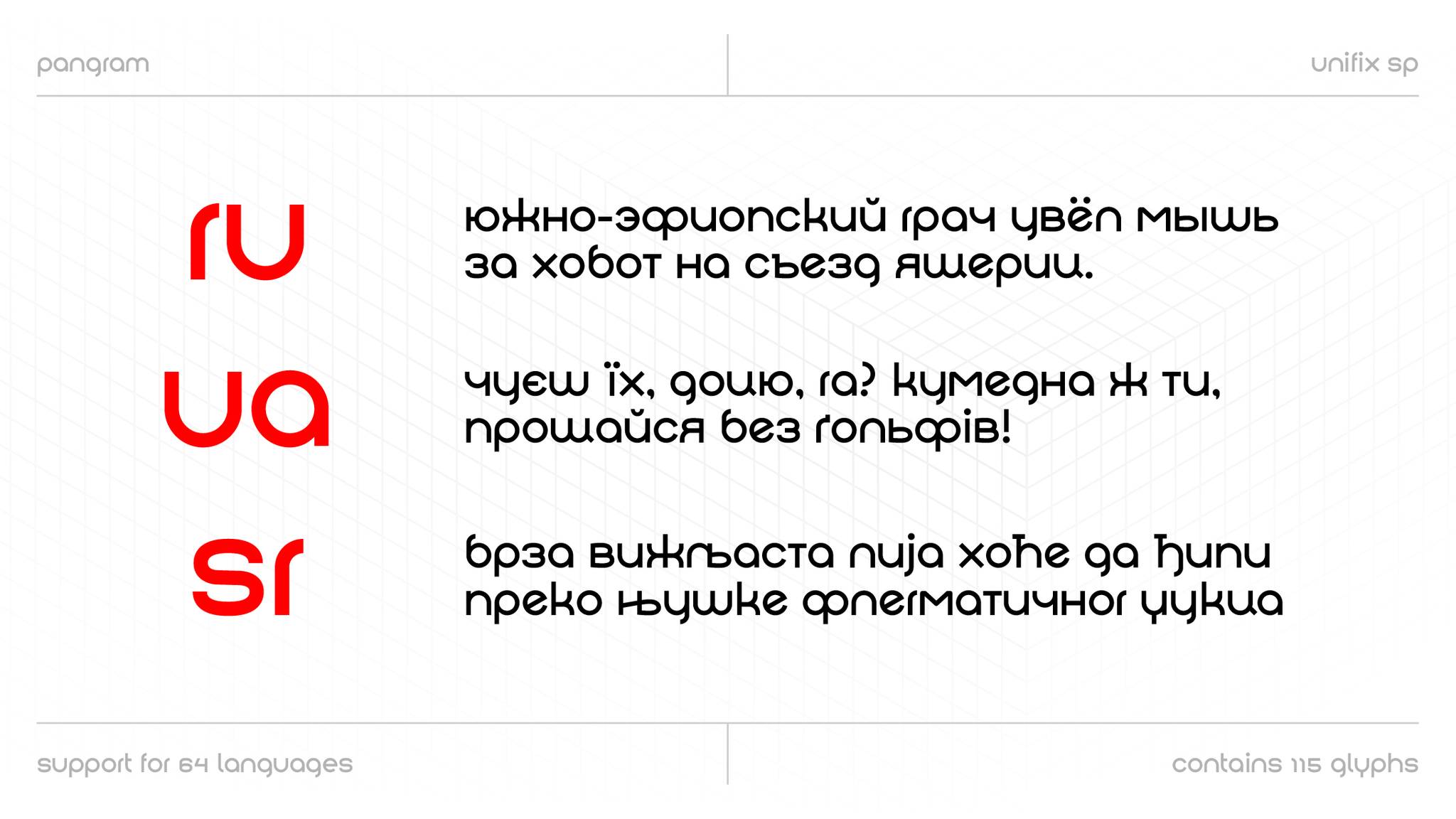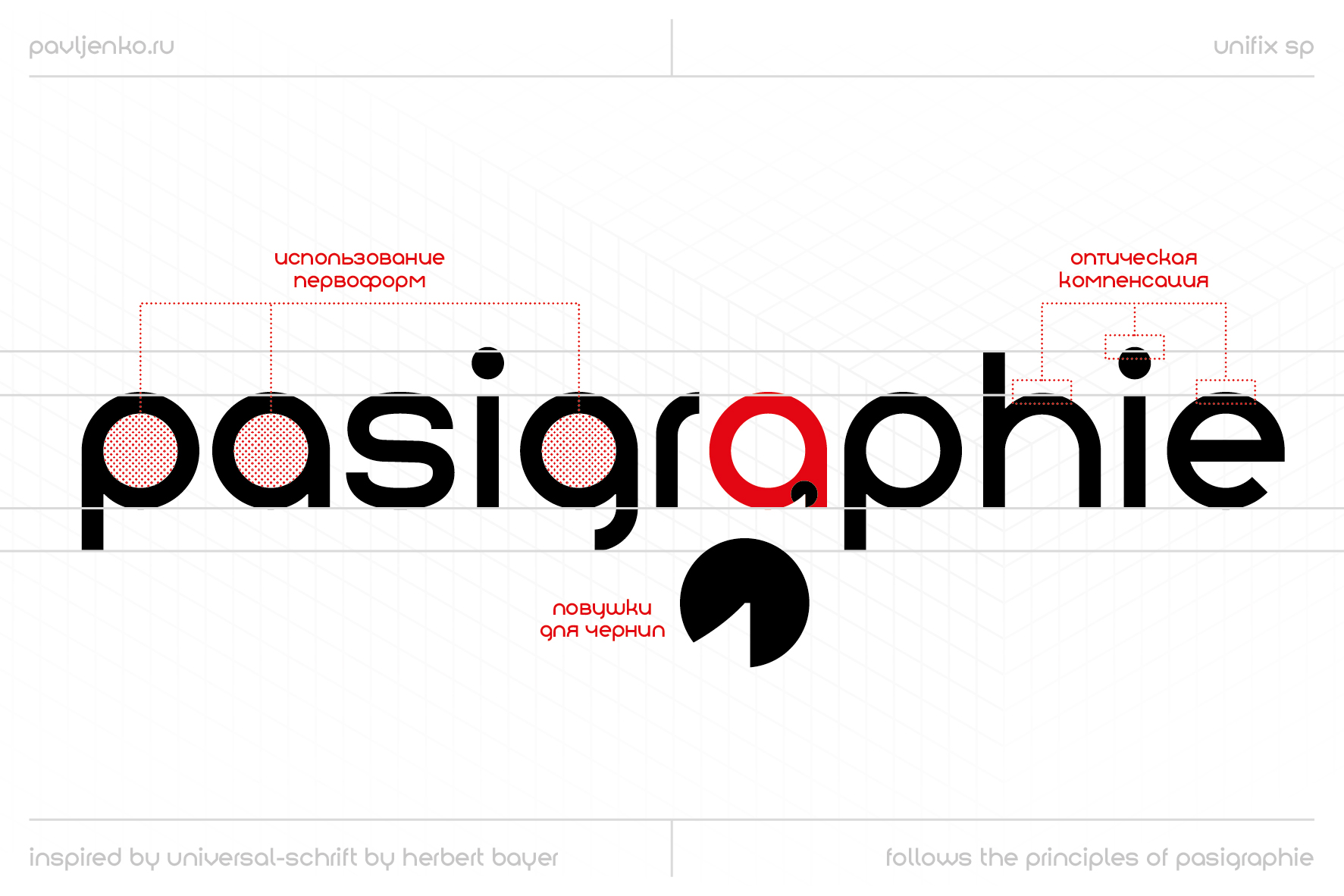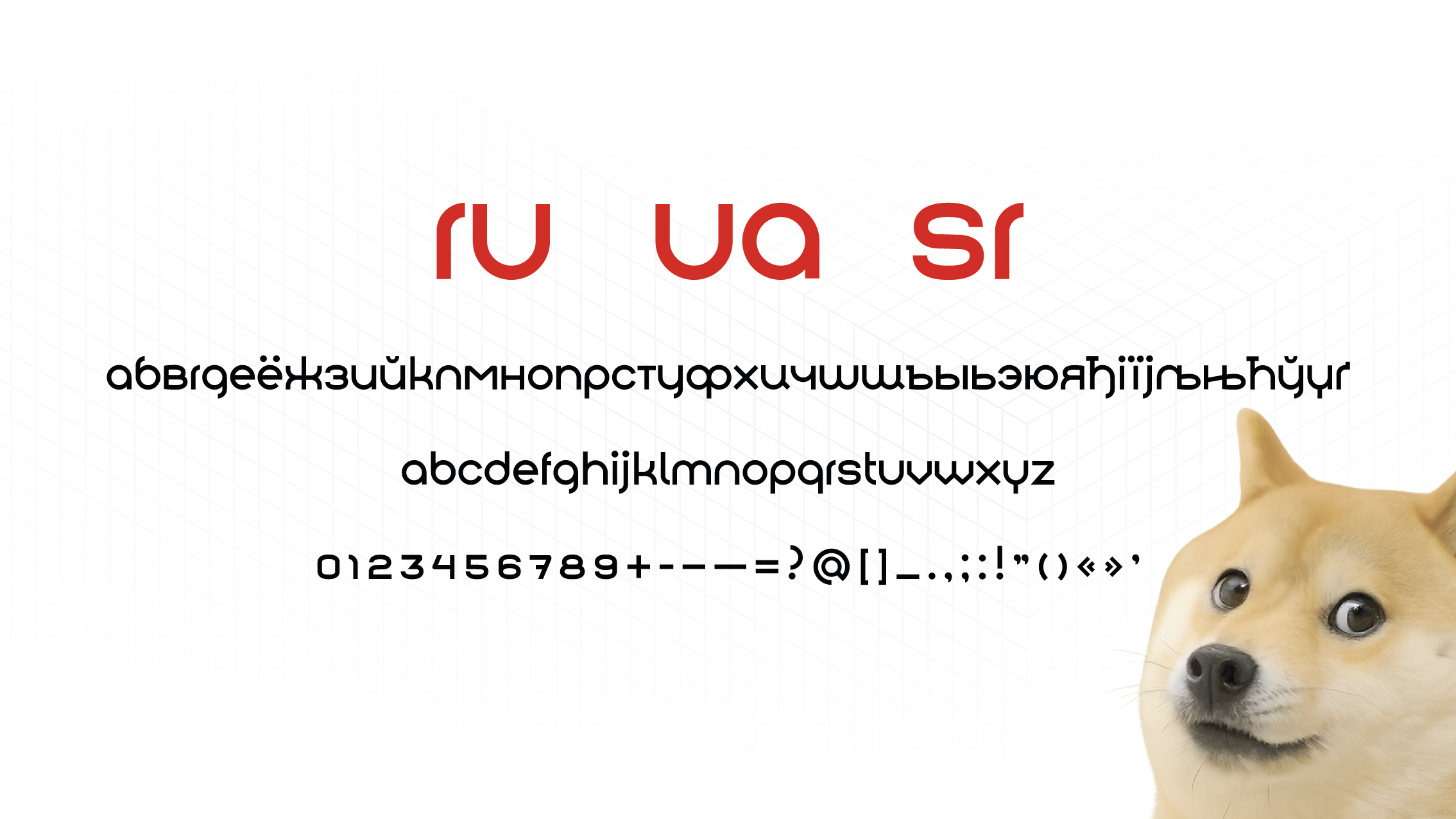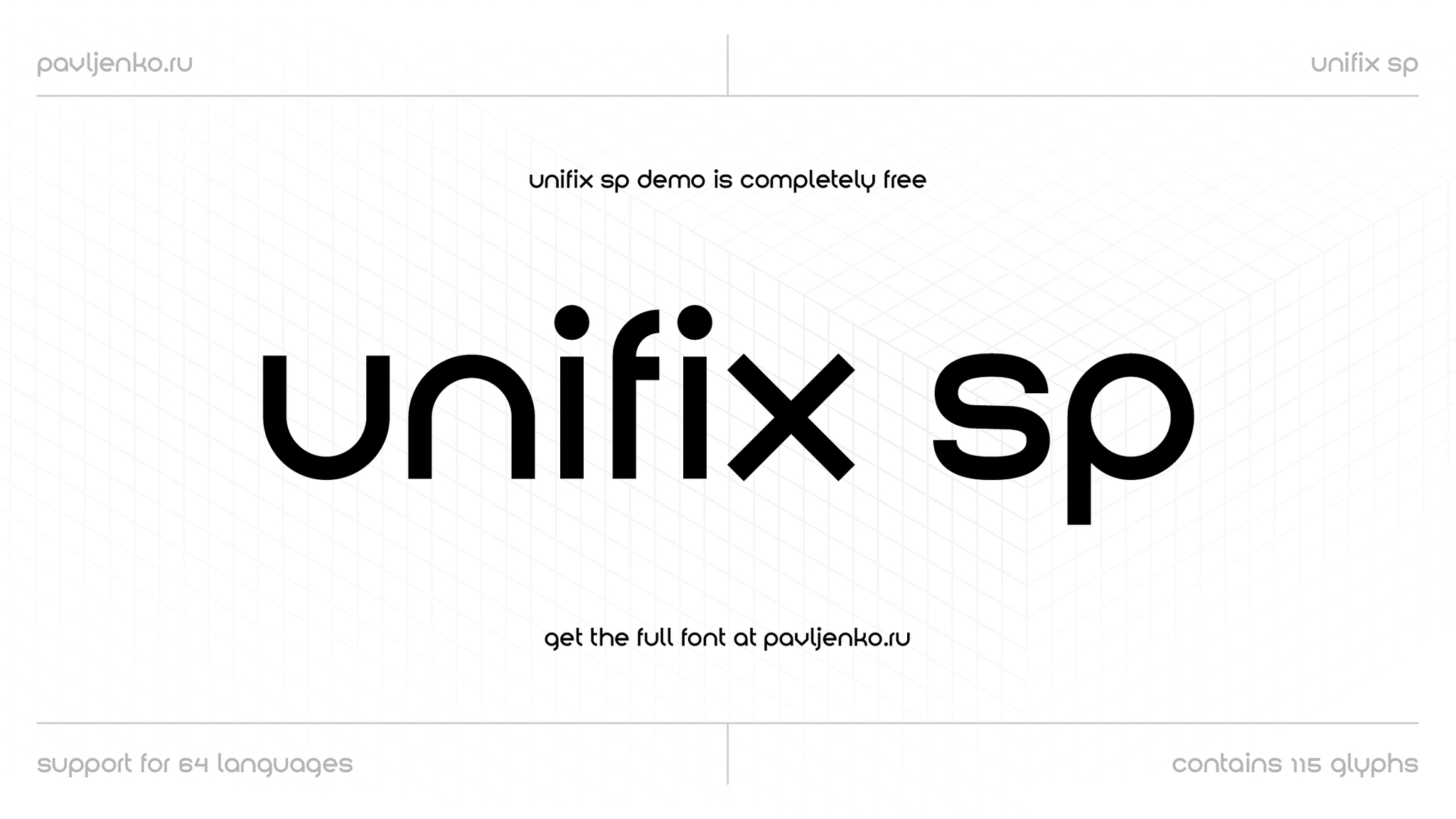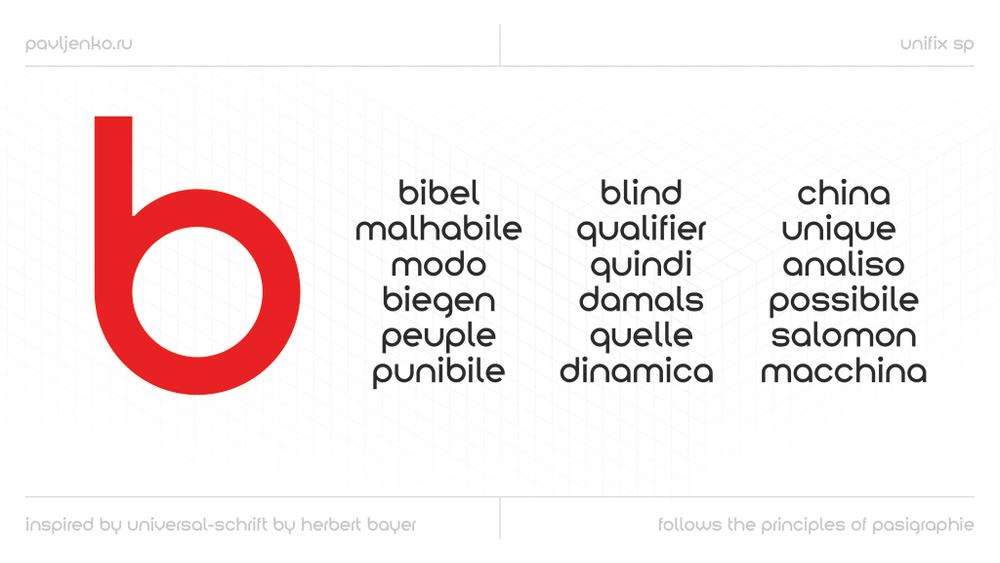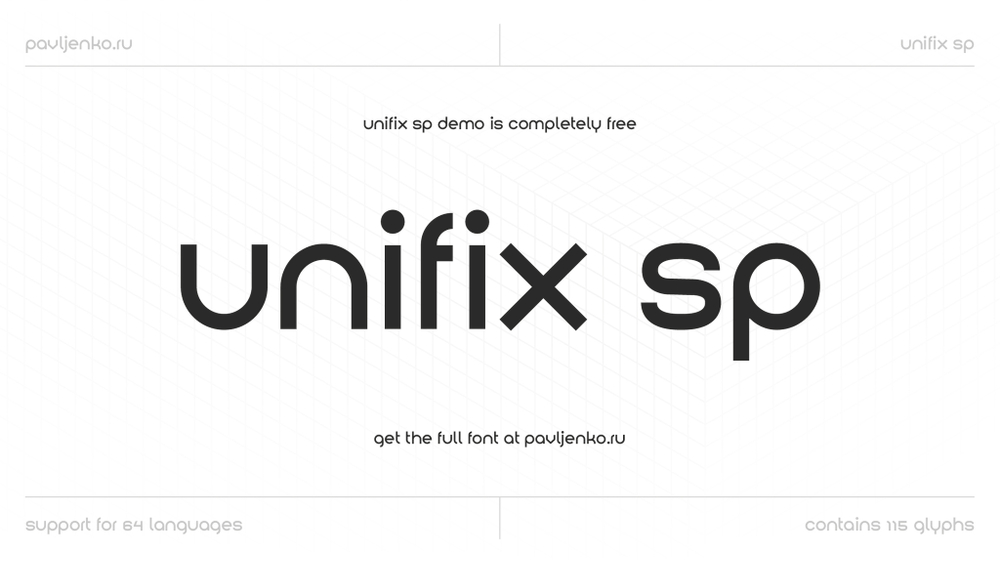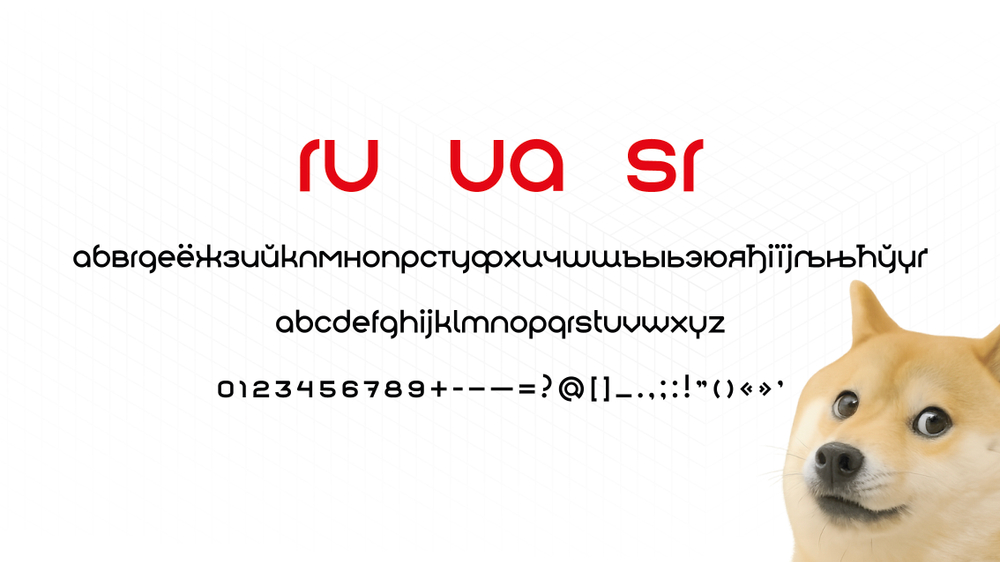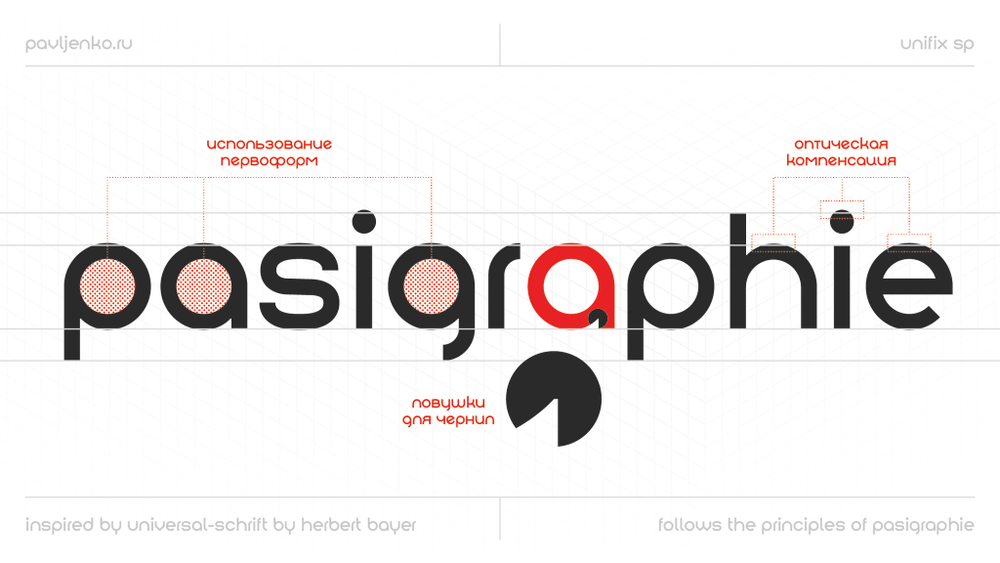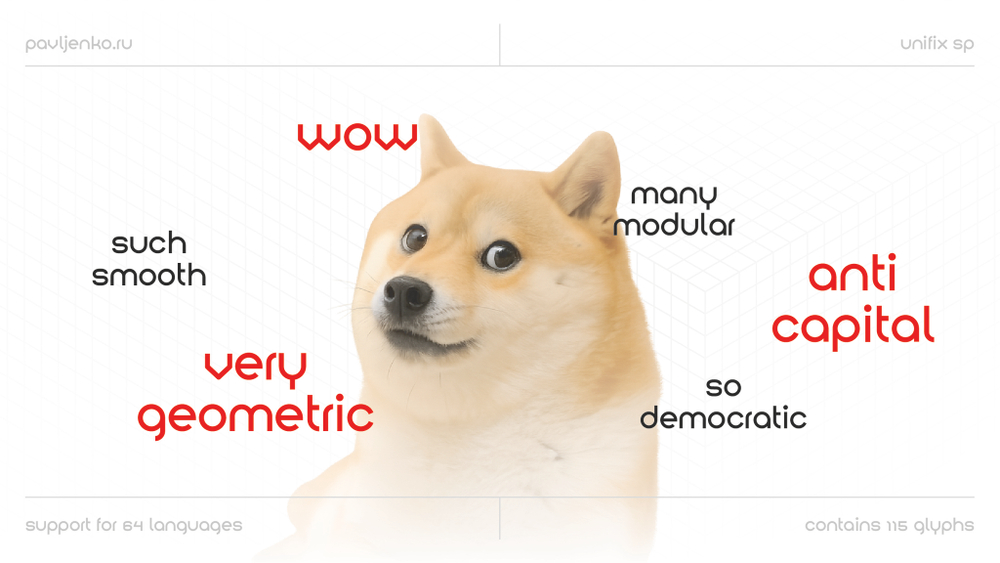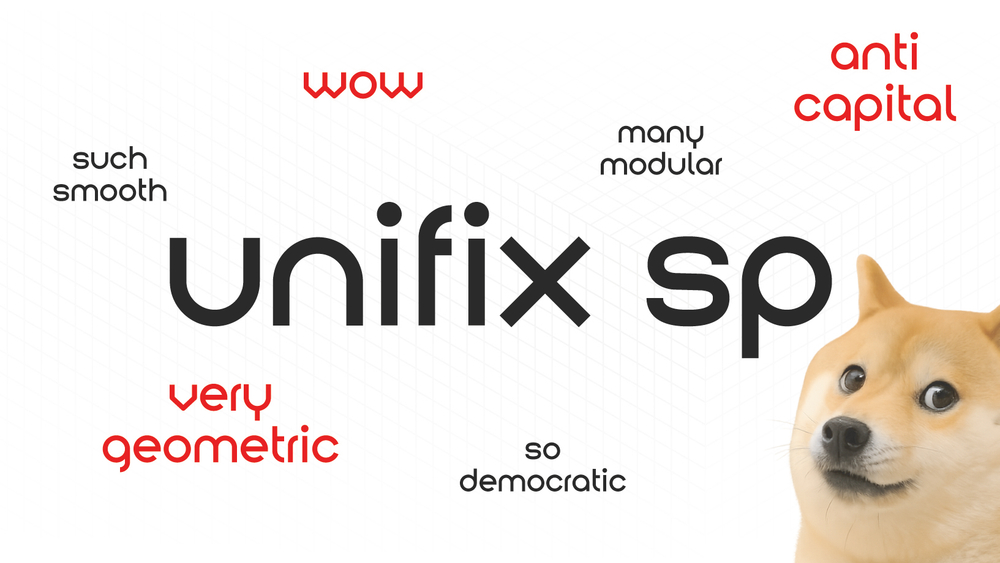
Шрифт Юнификс
Unifix — геометрический гротеск на первоформах, продолжающий идеи Герберта Байера о демократизации письма и его universal-schrift. Знаки собраны из круга и прямой, исторические детали и украшения сняты, поэтому набор читается спокойно и функционально. В логотипе, знаке и айдентике он звучит нейтрально: форма работает сама по себе и не отсылает зрителя к эпохе своего появления. В комплекте — полная версия STAR и лицензия.
Акцидентный шрифт
Шрифт без засечек, Баухауз, Bauhaus
Designer Sasha Pavljenko